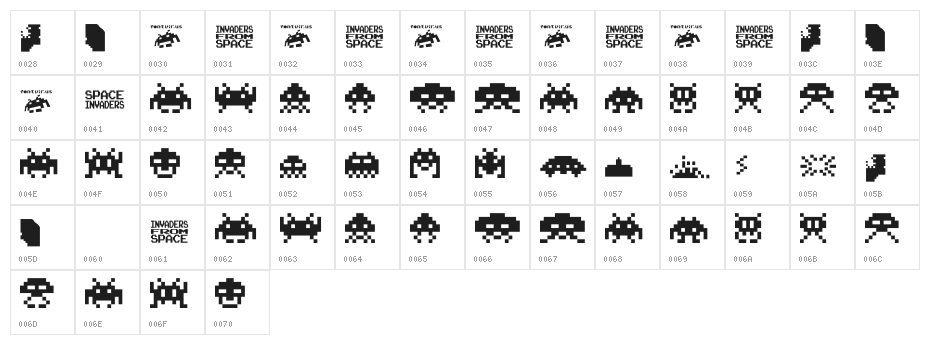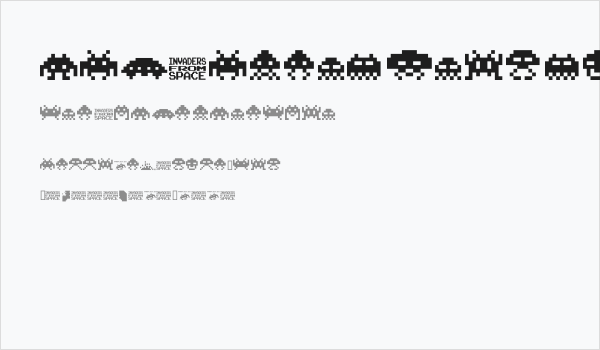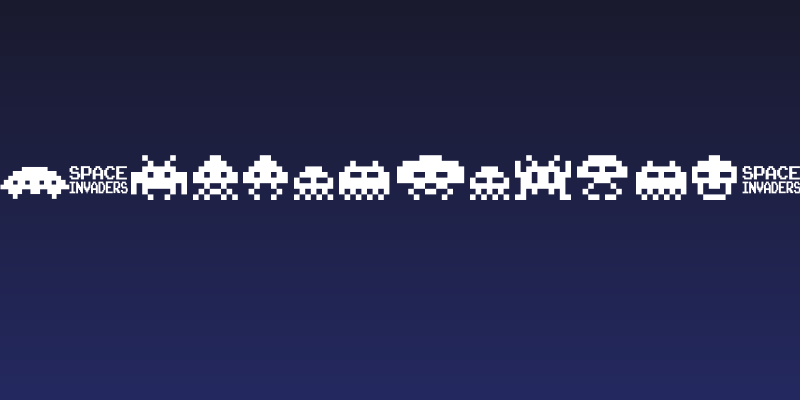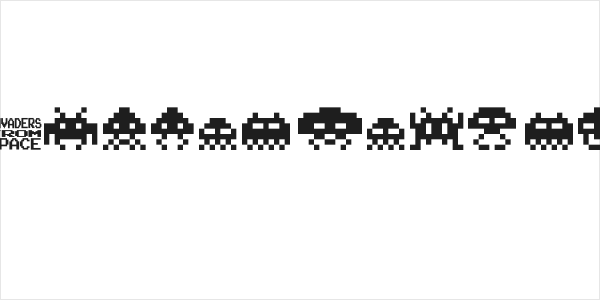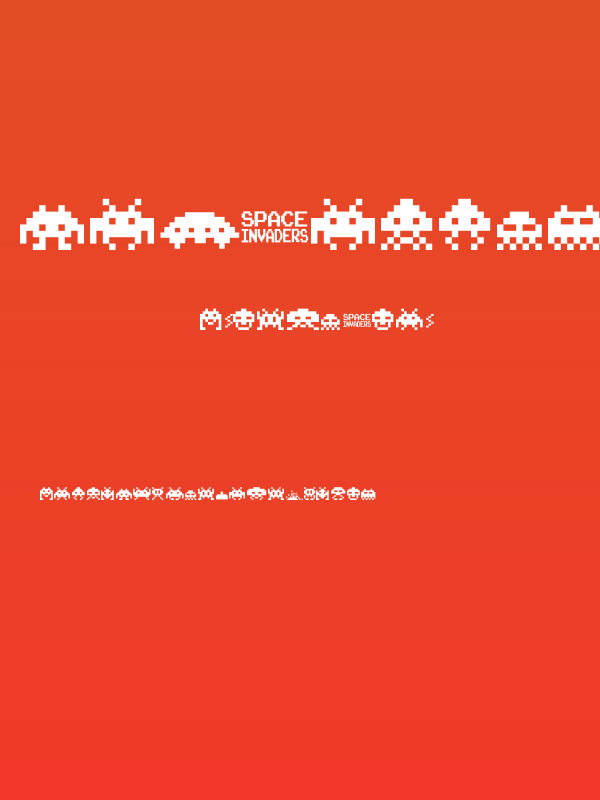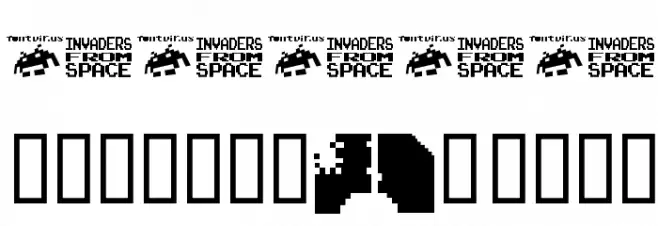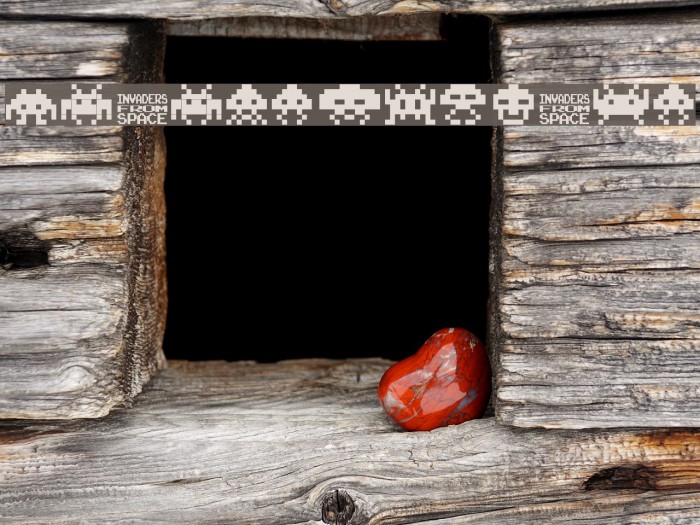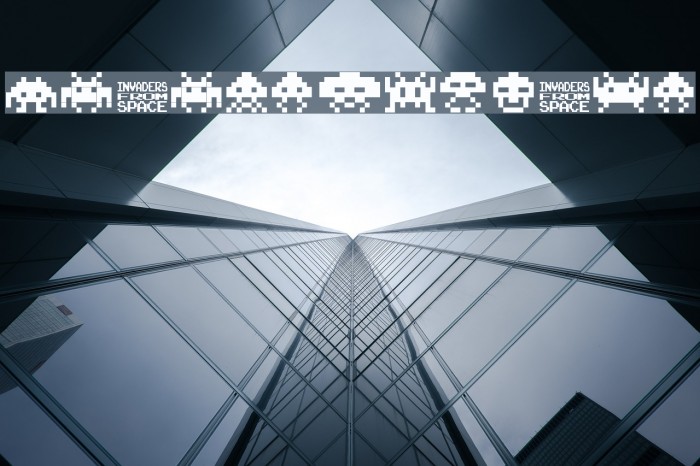
invanders from space Font
| النمط العام | Vintage |
| حالة الاستخدام | Logos, Posters, Themed Events |
| مشاريع مقترحة | Ideal for video game designs, retro-themed posters, and nostalgic branding projects. |